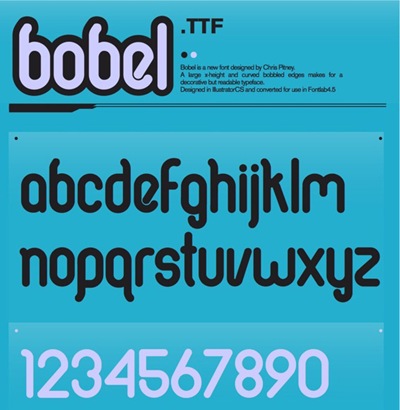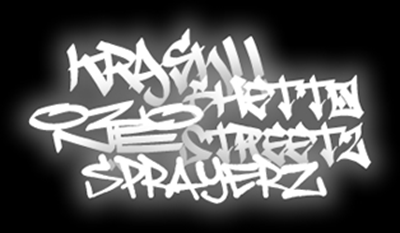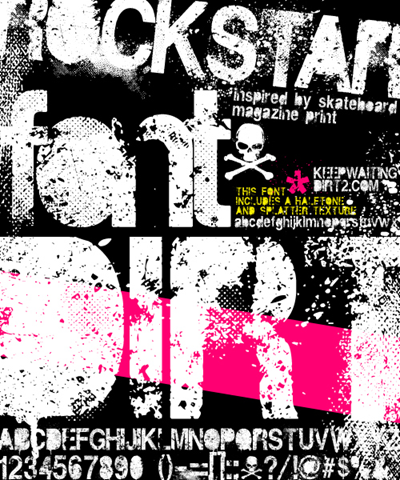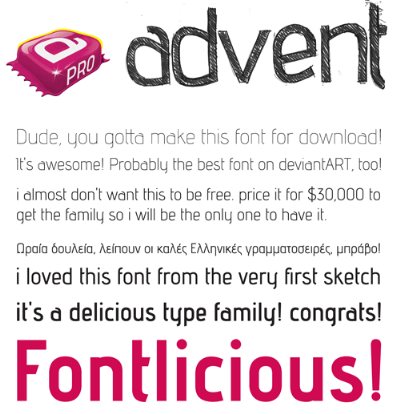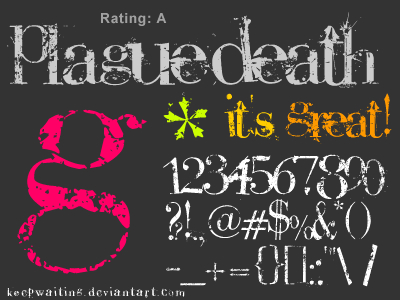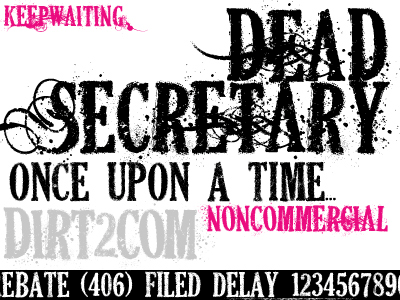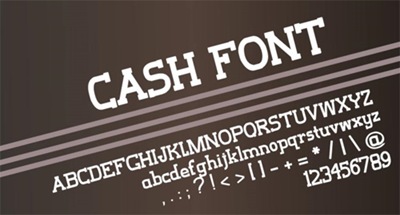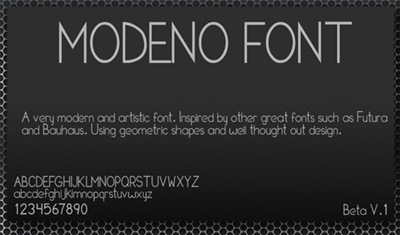
Бесплатные шрифты
Для создания логотипа или постера вам всегда понадобится подыскать подходящий шрифт. Мы решили сократить ваши затраты времени на поиски и предложить эту подборку. Надеемся вы сможете найти в ней то что вам пригодиться.
Шрифт в стиле гранж “DEAD SECRETARY” .ttf
Шрифт “Twilight” .ttf
Шрифт “Plague Death” .zip
Шрифт под названием “Ambrosia Font” .zip
Шрифт “Graffiti” .rar
Шрифт “Advent” .zip
Шрифт “Dirt 2 Death” .zip
Округлый шрифт “Bobel” .ttf
Шрифт под названием “Cash” .ttf
Шрифт “Modeno” .ttf